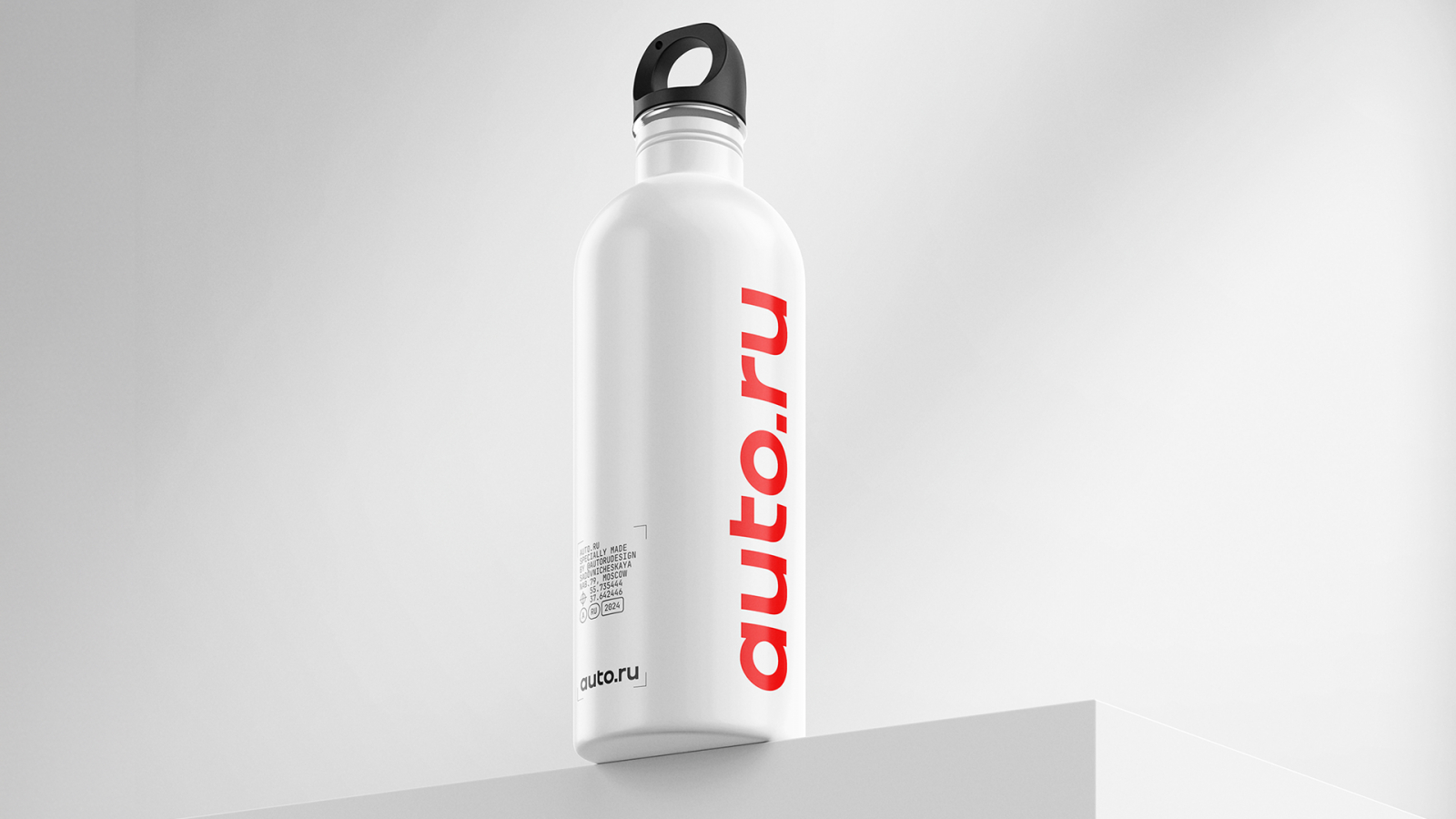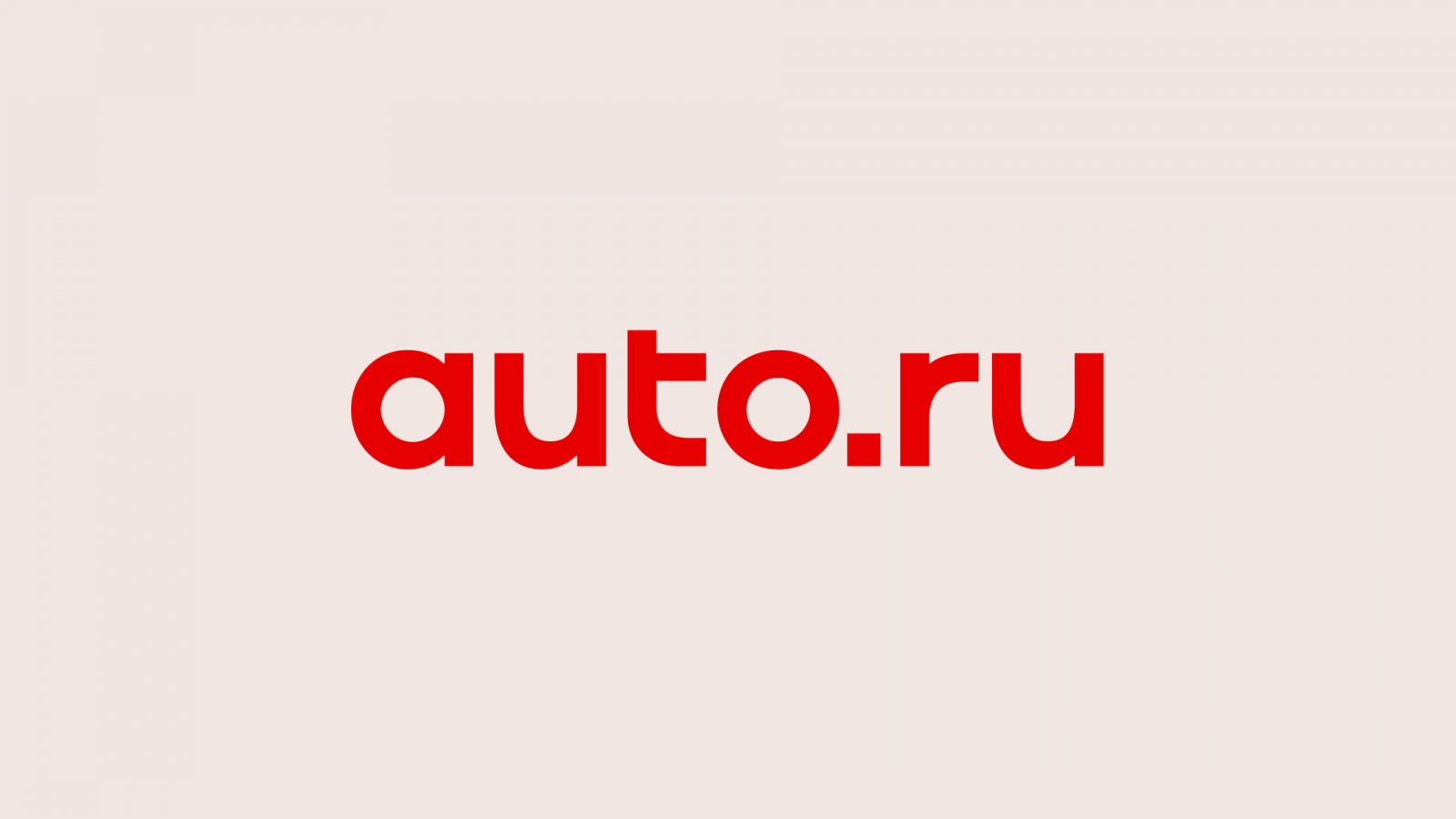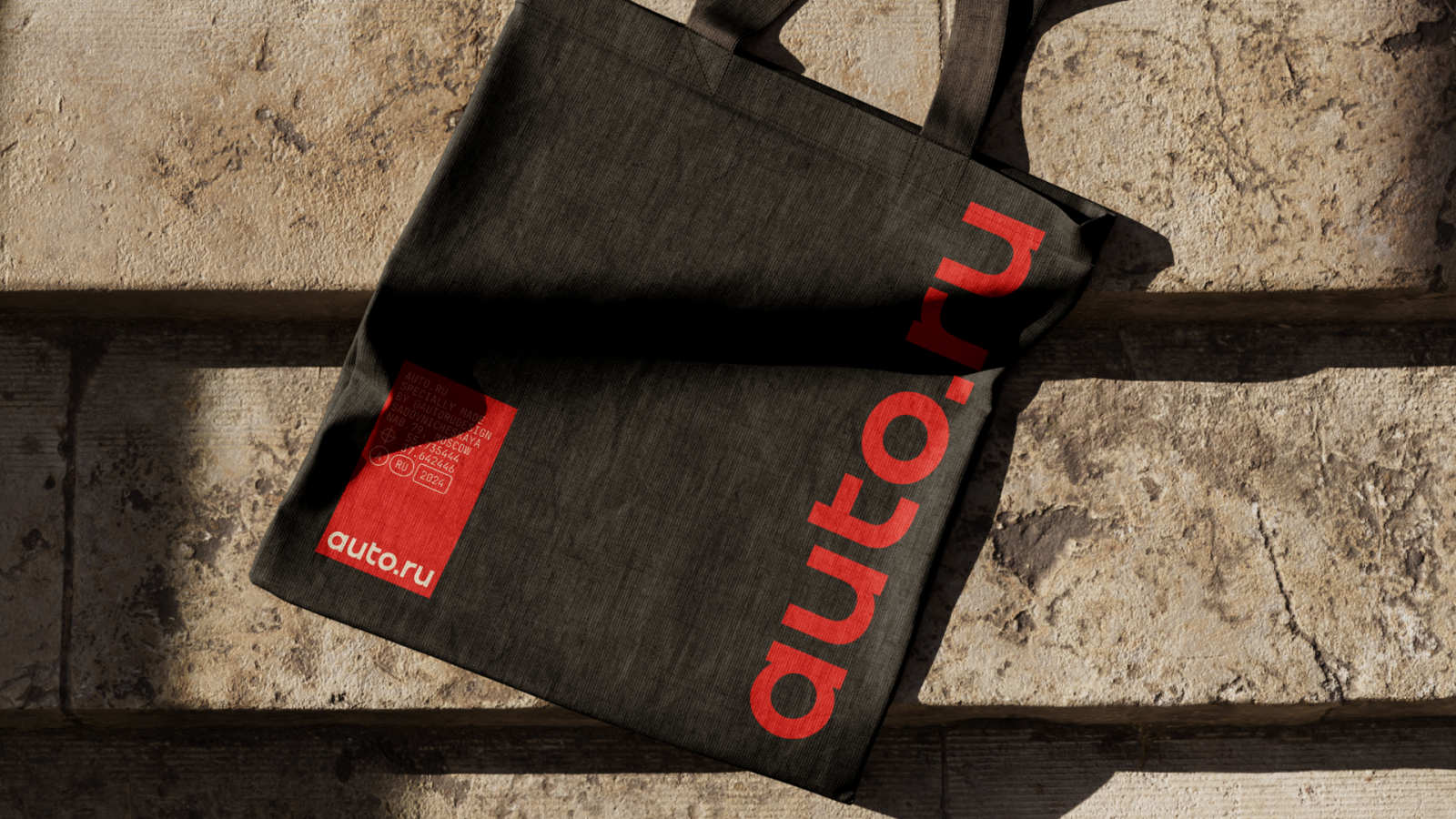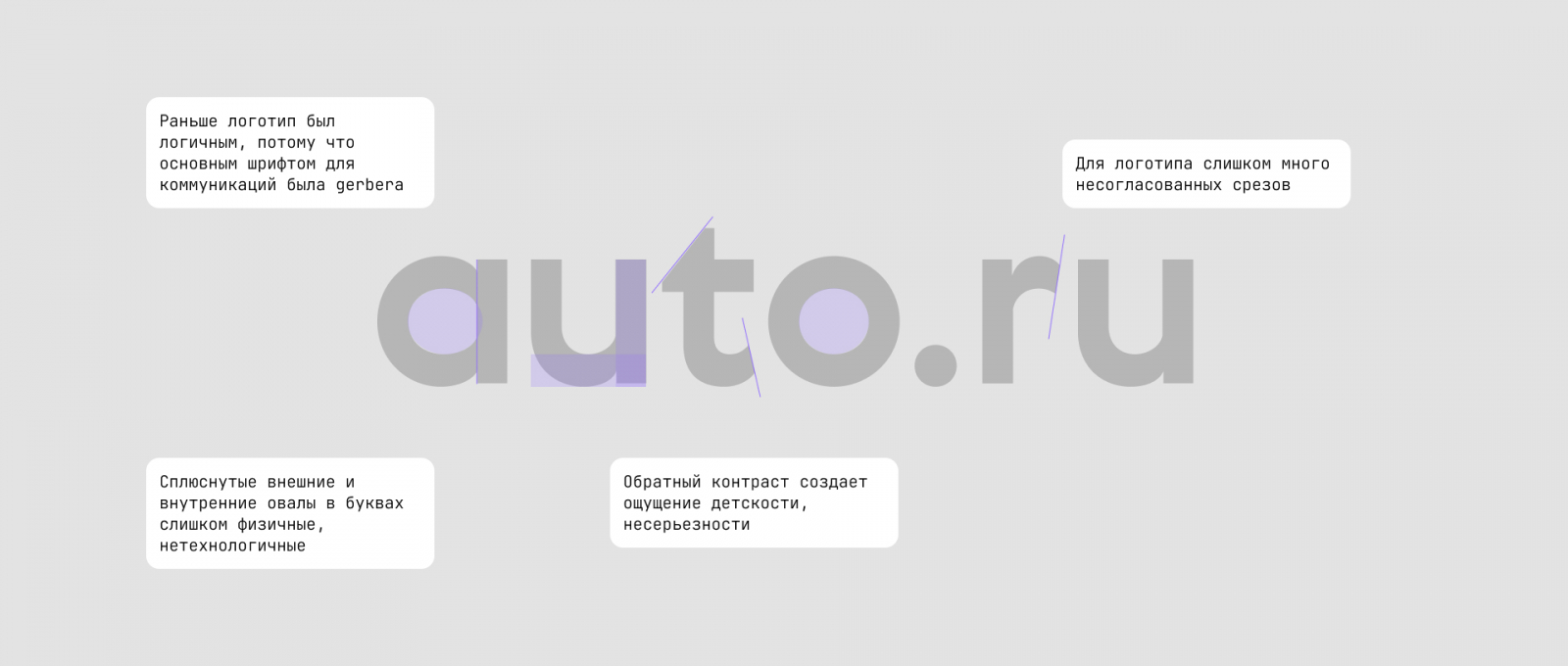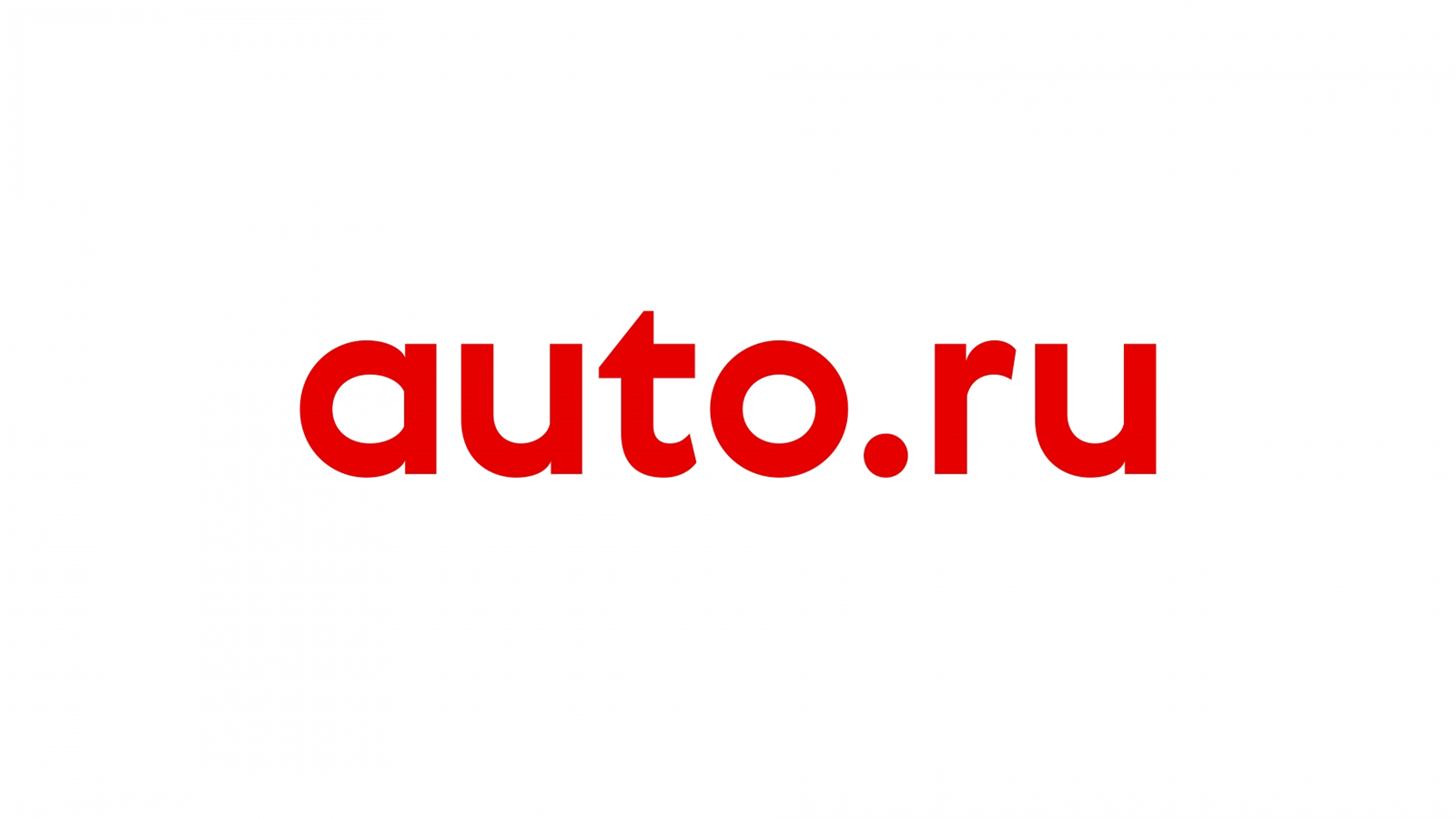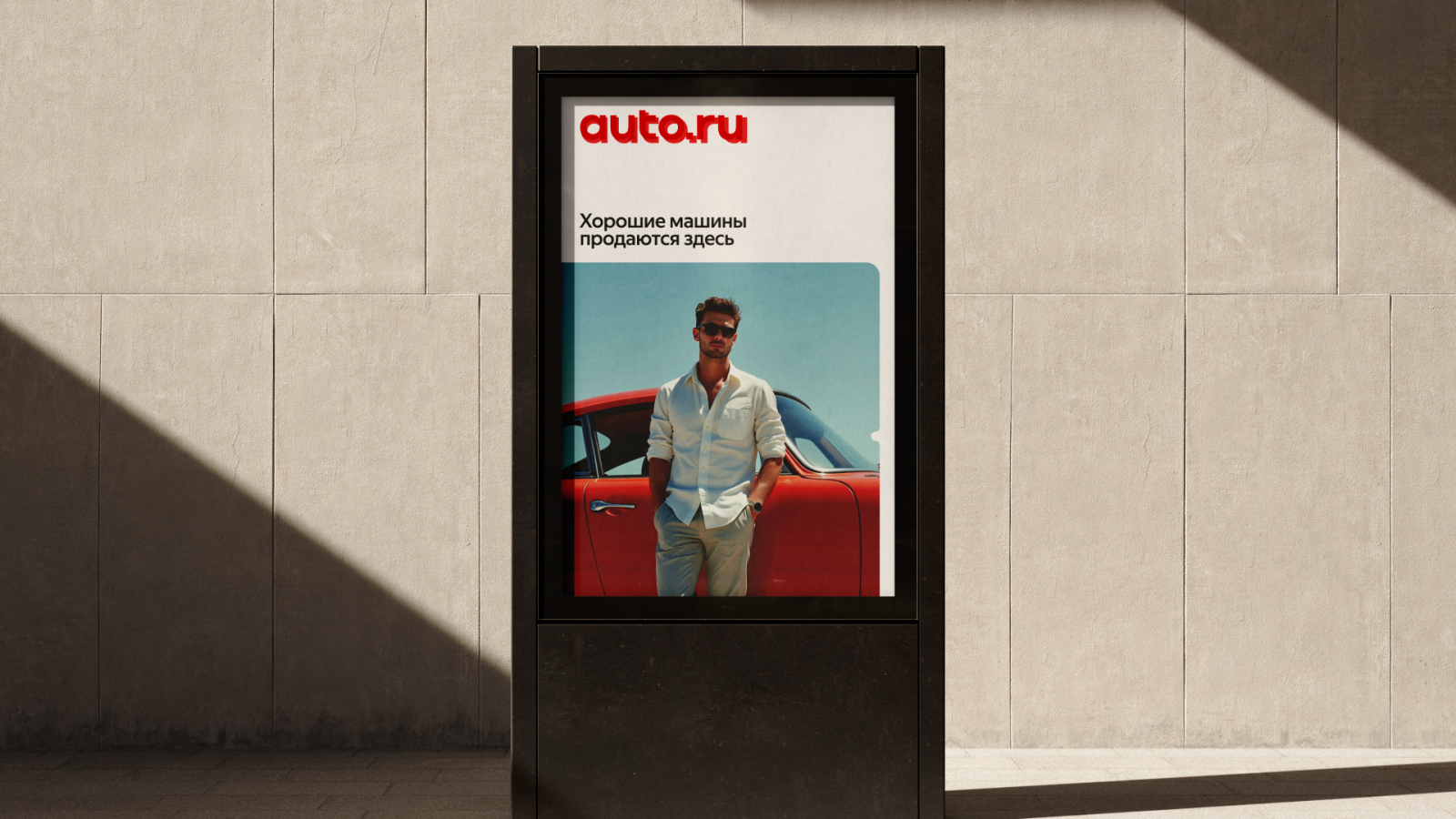
«Микроинженерия» логотипа и кастомный шрифт: «Авто.ру» провел редизайн
Компания создала компоненты модульной типографики
Российская онлайн-площадка «Авто.ру» для покупки и продажи машин провела редизайн: в нем объединили технологичность, автомобильную эстетику и историческую преемственность.
«Авто.ру» работает с 1996 года. За почти 30-летнюю историю логотип «с машинкой» стал узнаваемым маскотом, а сочетание открытого красного и белого цветов — частью ДНК бренда.
К 2025 году команда сервиса поняла, что бренду нужно новое звучание — более современный «инженерный» дизайн, который подчеркнет экспертизу в автоиндустрии, а также сделает визуальную айдентику ближе и понятнее для новых сегментов аудитории.
Компания провела редизайн инхаус. Была поставлена задача изменить айдентику, не меняя ее. Надпись Auto.ru и силуэт машины — визуал, закрепившийся с 1996 года: на старте это был автомобиль Бенца. Постепенно айдентика двигалась в сторону минимализма и мгновенной узнаваемости — логотип несколько раз переосмысливали, доводя до плакатной ясности.
Предыдущий лого, который создала команда «Авто.ру», хорошо работал в своих реалиях, но в мельчайших нюансах стал выглядеть устаревшим. Мешала несовершенная геометрия букв и обратный контраст (когда горизонтальные линии в буквах толще вертикальных) — в этом чувствовалась некоторая «детскость».
Команда стремилась сохранить цельный образ айдентики, но доработать ее в деталях, чтобы она передавала свежие эмоции: технологичность, постоянное развитие и легкость. Было важно подчеркнуть «автомобильный» характер бренда, чтобы он считывался на интуитивном уровне.
Специально для логотипа команда создала кастомный шрифт. Под шапкой бренда «Авто.ру» работает множество сервисов и суббрендов — и каждому нужна своя визуальная айдентика, увязанная с общим каноном. Логотип должен был гармонично сочетаться с основным шрифтом компании — Yandex Geo.
В результате возникли четкие вертикальные срезы, плавные скругления и оригинальная буква t со «спойлером». Вертикальные срезы использовали и в тех буквах, где традиционно это не принято: например, в кириллической «к». Они помогли добиться динамики, напоминающей о стремительных линиях кузова. В итоге логотип стал более ровным и «геометричным», что добавило чувство порядка и серьезности.
Кастомный шрифт потянул за собой изменения во всем визуальном коде бренда. В новой айдентике должна была легко считываться отсылка к автопрому, поэтому команда разработала особые «штампованные» плашки. Они словно выдавлены прессом, как детали на конвейере: скругленные углы и четкие вырезы вызывают ощущение машинной точности. Плашки стали универсальным контейнером для текстов, изображений и видео и при необходимости могут масштабироваться под любой формат или устройство.
Чтобы редизайн получился, важно было создать полноценную визуальную среду, а не отдельные элементы. Так появились компоненты модульной типографики, вдохновленные маркировками на автомобильных деталях.
Теперь координаты, иконки и короткие технические надписи выглядят так, словно взяты из чертежей конструкторского бюро. Это подчеркивает, что «Авто.ру» — не просто доска объявлений, а сервис с глубокой экспертизой в мире машин, объединяющий настоящих «автоадептов».
Команда сохранила исторический для бренда красный цвет, ощущение доступности и открытости, а все обновления произошли за счет дизайнерской «микроинженерии».
Визуальный код приобрел серьезную технологичность, которая читается в кастомном шрифте, «штампованных» графических элементах и динамичных компонентах модульной типографики. Новую айдентику протестировали на всех устройствах — редизайн получился эффектным, изящным и практичным.